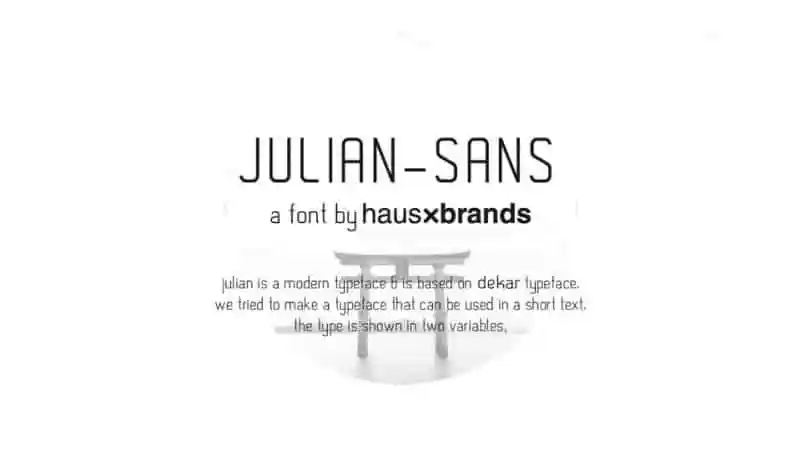
A Julian Sans Serif Font é uma opção ideal para designers que valorizam um estilo moderno e minimalista com toques retrofuturistas. Criada pelo designer fontes Hausxbrands, esta tipografia aderiu-se à famosa fonte Dekar, mantendo seu legado enquanto oferece características frescas e atemporais. Ideal para textos curtos, projetos de revistas e identidades visuais, a Julian Sans Serif pode ser usada em uma vasta variedade de aplicações. Seu design moderno permite que seja facilmente personalizado por meio de duas variações, tornando-a um recurso versátil para qualquer projeto editorial ou digital que deseje dar um toque único e contemporâneo. Engane-se se pensa que a Julian Sans Serif é apenas uma fonte simples; ela traz consigo uma mistura perfeita de história e modernidade, adaptável tanto à linha clara quanto ao texto rico.